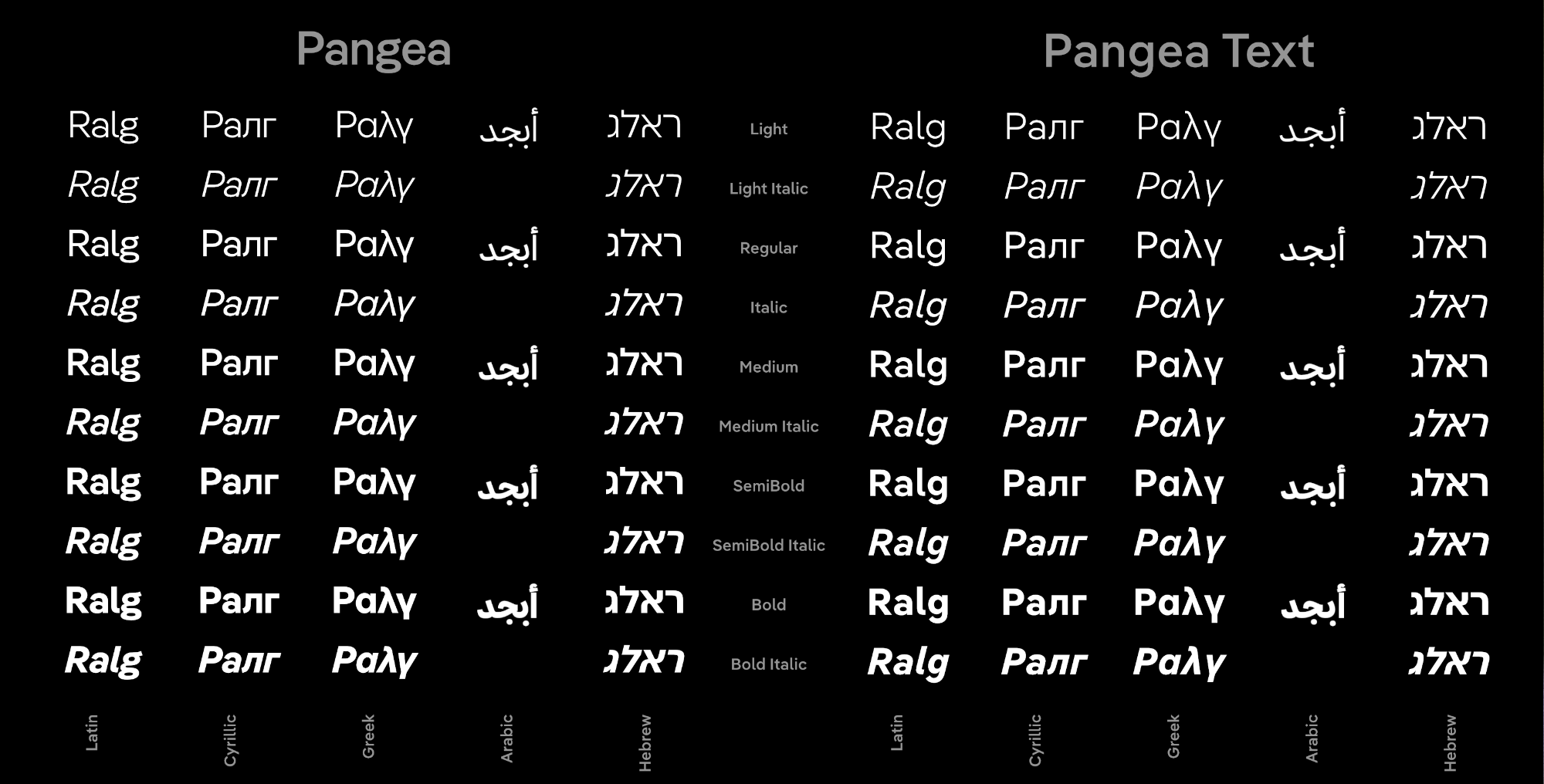
- 2020
- sans
- Antiqua geometrisch
- Versaleszett:
- enthalten
Die Pangea ist eine geometrische Grotesk von Christoph Koeberlin und erschien ab 2020 bei Fontwerk. Die Schrift ist als Pangea und Pangea Text für Fließtextanwendungen erhältlich. Als Ableger sind die Familien Pangea Afrikan und Pangea Afrikan Text erhältlich. Die Schrift unterstützt über 500 Sprachen und enthält neben der lateinischen Belegung auch kyrillische, griechische (nur monotonische), arabische und hebräische Zeichen. Für den lateinischen, kyrillischen und griechischen Teil stehen drei engere Weiten zur Verfügung: SemiCondensed, Condensed und XCondensed.